Üç Ana Yazı Tipi Türü
Yayınlanan: 2023-01-03Yazı tipi, bir dizi harf, sayı veya sembolden oluşan bir grafik tasarımdır. Üç ana yazı tipi türü vardır: vektör, bitmap ve kontur. Vektör yazı tipleri, en sık kullanılan yazı tipi türüdür. Kaliteden ödün vermeden herhangi bir boyuta ölçeklenebilen bir dizi vektör şeklinden oluşurlar. Bit eşlem yazı tipleri, bir ızgara üzerinde belirli konumlara eşlenen bir dizi pikselden oluşur. Kontur yazı tipleri, her karakteri oluşturmak için kullanılan bir dizi konturdan oluşur.
Ölçeklenebilir Vektör Grafikleri (SVG) dosyası, küçültülebilen ve büyütülebilen tek bir dosyadır. SVG yazı tipi olarak bilinen OpenType biçiminin yeni bir sürümü artık mevcut. Bu format kullanılarak tüm karakterler çeşitli renklerde ve şeffaflıklarda görüntülenebilir ve hatta bazıları canlandırılabilir. Bu nitelikler, standart OTF ve TTF biçimleri kullanılarak oynatılamaz. OpenType-SVG yazı tipleri, normal yazı tipleri olan .ttf ve.otf ile aynı dosya uzantılarına sahiptir, ancak dosya uzantısı yapısında farklılık gösterirler. Bu yazı tipinin rengini Katmanlar menüsünden seçerek değiştirebilirsiniz. Metin katmanına sağ tıkladıktan sonra Karıştırma Seçenekleri iletişim kutusu görünecektir.
Renk Yerleşimi seçeneği açılır pencerede bulunabilir. Ayarlara gitmek için tıklayın. Birden çok yazı tipine sahip birden çok katmanınız olduğunda, Photoshop'ta yazı tipinin renk aralığını korumak kolaydır. Dönüştürmenize izin veren çevrimiçi araçlar var. IcoMoon ve Fontello gibi yazı tipi simgelerine VNG dosyaları. Bu yöntem, kendi özel yazı tiplerinizi kullanarak sva'da bir yazı tipi dosyası oluşturmak için de kullanılabilir. Her karakter için, Adobe Illustrator veya Adobe Photoshop kullanılarak vektör veya bitmap biçiminde çizilebilir.
Bir SVG yazı tipi, şeffaflık ve renk bilgileri gibi yazı tiplerinin asla ekleyemediği şeyleri içeren Açık Yazı biçiminin yeni bir sürümüdür. Fırça darbelerine benzeyen yazı tiplerinde ve yarı saydam alanlara sahip yazı tiplerinde iyi çalışırlar.
Simge yazı tipleriyle karşılaştırıldığında , SVG'ler daha fazla uyarlanabilir. Yapabileceğiniz ilk şey, sva şablonlarıyla daha fazla renk eklemektir. Tek renkli simgelerle karşılaştırıldığında, SVG simgeleri gradyan efektleri sağlar. Ek olarak, bir simge, SVG formatında tek tek vuruşlarla canlandırılabilir.
Bir Yazı Tipi Svg Olabilir mi?
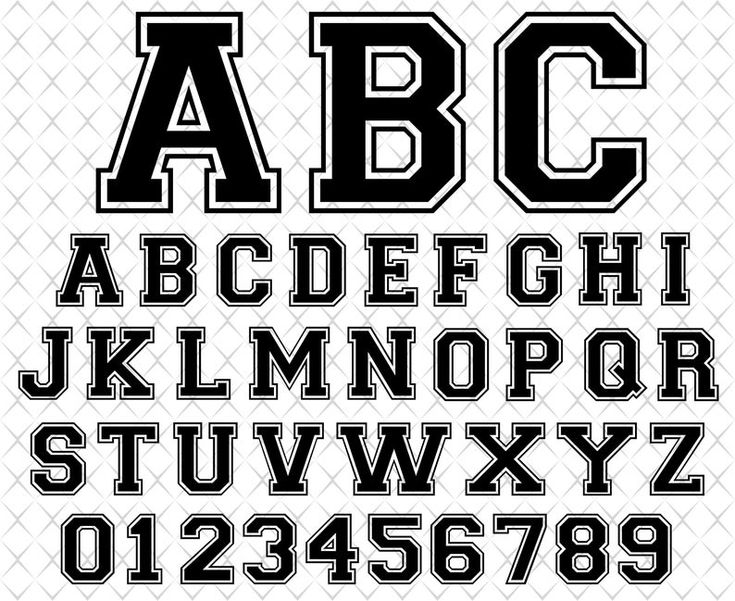
Bir OpenType yazı tipi olan Scalable Vector Graphics (SVG) formatı, kendisine bir SVG soneki ekleyen formatın yeni bir sürümüdür. SVG formatında karakterler farklı renklerde ve farklı şeffaflıklarda gösterilebilir ve hatta bazıları canlandırılabilir.
1999'da tanıtılan SVG 1.0'ın ilk sürümünün amacı, tasarımcıların grafikleri istedikleri herhangi bir yazı tipiyle tasarlamalarına ve tarayıcılarında doğru şekilde görünmelerine izin vermekti. svgs'de yazı tipi desteği nasıldır ve yazı tiplerinin içinde düzgün çalışmasını sağlamak için en iyi uygulama nedir? Çoğu büyük sistemde, web uyumlu yazı tiplerinin kullanılması, SVG yazı tiplerinin görüntülenmesini sağlar. Web uyumlu bir yazı tipi, tüm platformlar veya sistemlerle uyumlu olandır. Google yazı tipleri, Font Squirrel ve benzeri web yazı tipi sağlayıcılarının yükselişi nedeniyle, sVG'lerde web yazı tiplerini kullanmak hiç bu kadar kolay olmamıştı.
Hangi Yazı Tipi Uzantısı En İyisidir?
En uygun biçim olan WOFF 2.0, web üzerinde en popüler olanıdır. Ancak, bu yazı tipi grafik yazılımıyla uyumlu değildir.
Hangi Yazı Tipi Formatını İndirmeliyim?
OTF dosyalarına ihtiyacınız varsa, lütfen destek ekibimizle iletişime geçin; bunları sizin için elde etmek için çalışacağız. Web sitemizde, Windows ve Mac'te yazı tipi yükleme hakkında bilgiler bulacaksınız.
Bir seferde yalnızca bir yazı tipi biçimi yüklemeniz önerilir. Her iki yöntem aynı anda kullanılırsa istenmeyen sonuçlar ortaya çıkabilir. Microsoft ve Adobe Systems tarafından 90'ların ortalarında oluşturulan bir vektör yazı tipi biçimi türüdür. Formatın başarılı olması amaçlandı çünkü TTF formatına dayanıyordu. Bir OTF yazı tipindeki glif ana hatları verileri, Kompakt Yazı Tipi Formatında (CFF) veya TrueType formatında saklanabilir. Fontspring üzerinden satılan fontların neredeyse tamamı CFF versiyonundadır ancak site üzerinden satın alırsanız her iki formatı da ücretsiz olarak kullanabilirsiniz. Tüm modern tarayıcılar, temel web yazı tipi kitimize dahil olan WOFF ve WOFF2 dosya biçimlerini destekler.
Neden Truetype (.ttf) Üzerinden Opentype Yazı Tiplerini (.otf) Kullanmalısınız?
Çok çeşitli bağlamlarda kullanılan bir yazı tipi biçimidir. Veri türleri için bir TrueType alt alanı (uzantısı olan) kullanılırken, veri türleri için bir TrueType alt alanı kullanılır. Ttf (Transmission Field) ve CFF (Cortical Field) iki farklı sinyaldir. Tasarımcı Ofisi (OTF), tasarımcıların ve dizgicilerin bir parça üzerinde değişiklik yapmasına ve daha iyi görünmesini sağlayan daha fazla özelliğe sahip, daha sağlam bir uygulamadır. Dosya, OTF dosyasıyla yazı tiplerini kullanan tüm modern uygulamalar tarafından kullanılabilir. TTF yazı tipi dosyaları internette ücretsiz olarak mevcuttur ve ayrıca OTF ve WOFF gibi diğer yazı tipi biçimlerine dönüştürülebilir. Duruma göre yükleyebilir veya kaldırabilirsiniz. Bu sadece sizden sadece bir tane varsa olur. Dosyayı yükledikten sonra kullanabileceksiniz. Ayrıca, bir TTF dosyası virüsler tarafından bozulamadığı için kurulumu daha kararlıdır. Bir yazı tipi dosyası pasif bir dosya olduğu için, Menhir 3 yıl önce virüs içermesinin hiçbir yolu olmadığını yazmıştı. Virüs yürütülebilir (exe) dosyasına dahil edildiğinde, yalnızca kendini etkinleştirir.
Svg Olarak Kaydettiğimde Yazı Tipim Neden Değişiyor?
Bunun birkaç olası nedeni vardır: 1. Kullanmakta olduğunuz yazı tipi hedef sistemde mevcut değil. SVG olarak kaydettiğinizde, dosya XML'e dönüştürülür, bu da yazı tipi bilgisinin de dönüştürüldüğü anlamına gelir. Hedef sistemde aynı yazı tipi yüklü değilse, farklı bir yazı tipinin yerini alacaktır. 2. Kullanmakta olduğunuz yazı tipi bir yola dönüştürüldü. Bazı yazı tipleri, özellikle yaygın olarak kullanılmayanlar, vektör şekilleri olarak mevcut olmayabilir. Bu durumda yazı tipi, farklı bir görünüme neden olabilecek bir dizi yola dönüştürülür. 3. Kullanmakta olduğunuz yazı tipi SVG dosyasına katıştırılmıştır. Bu, yazı tipi bilgisinin dosya içinde saklandığı ve dosyayı açan herhangi bir sistemde kullanılacağı anlamına gelir. Ancak dosya, yazı tipinin gömülmediği duruma göre daha büyük olacaktır.
Svg Yazı Tipleri: Yazı Tipi Teknolojisinin Sonraki Dalgası
Yazı tipleri dünyasında, her biri benzersiz özelliklere sahip birkaç SVG yazı tipi türü vardır. SVG, Ölçeklenebilir Vektör Grafikleri (SVG) biçimi olduğundan, karakterlere gömülü birden çok renk, degrade görüntü veya desen içerebilir. Photoshop'ta Metin Aracını (T) seçin, bir form doldurun ve ardından içeriğinizi ekleyin. Araç çubuğunu seçerek, istediğiniz herhangi bir SVG yazı tipini seçebilirsiniz. Bunun için bir yazı tipi seçtikten sonra nasıl çalıştığını deneyebilirsiniz. Örneğin, çeşitli özellikler etkinleştirildiğinde metnin nasıl görüneceğini görmek için metni seçebilir ve SVG yazı tipinin Önizleme düğmesine tıklayabilirsiniz. SVG yazı tipleriyle metninize biraz parlama eklemek, biraz daha fazla yaratıcılık katmanın harika bir yoludur ve biraz daha fazla yaratıcılık gerektiren herhangi bir projeye mükemmel eklemeler yaparlar. Yeni bir yazı tipi teknolojisi arıyorsanız, bir SVG yazı tipine göz atmak isteyebilirsiniz.